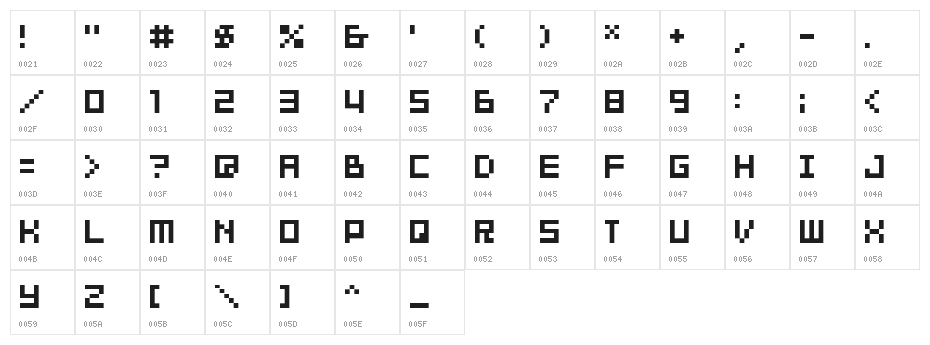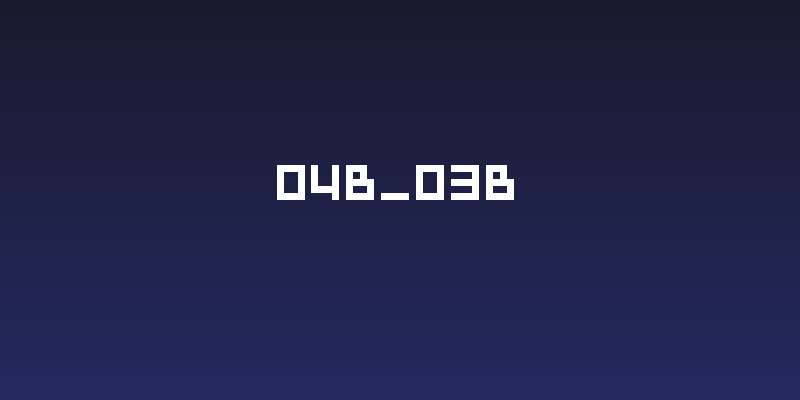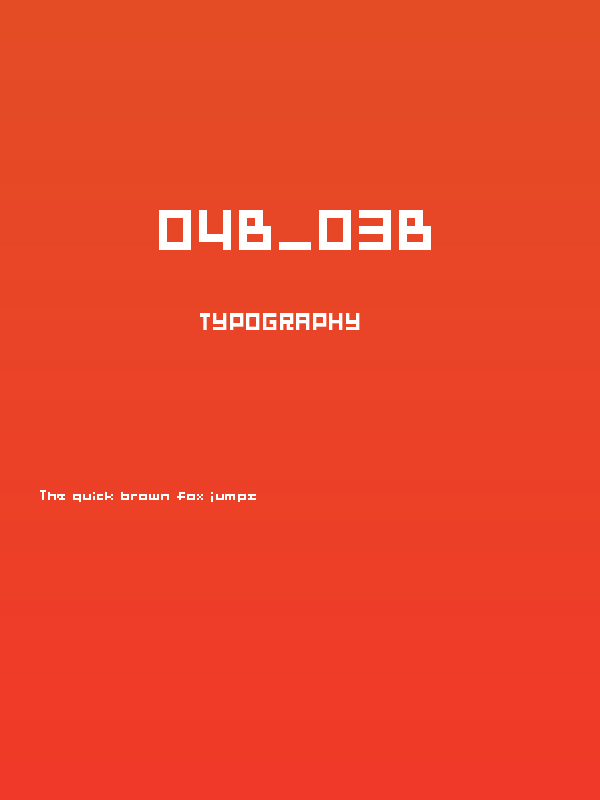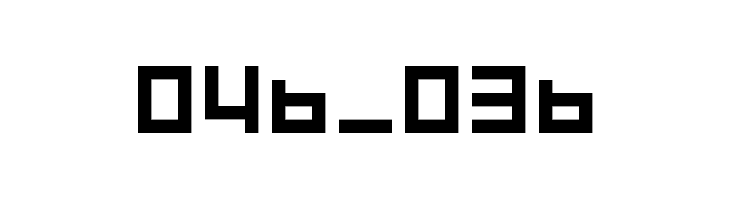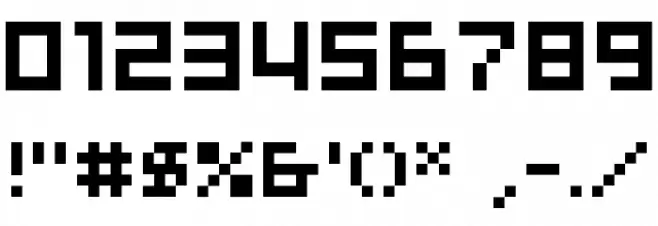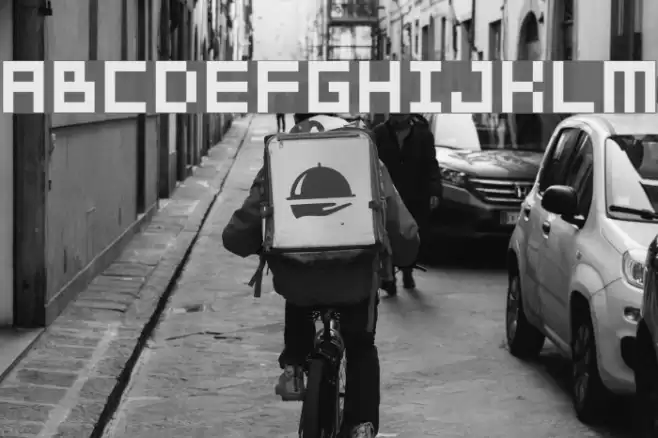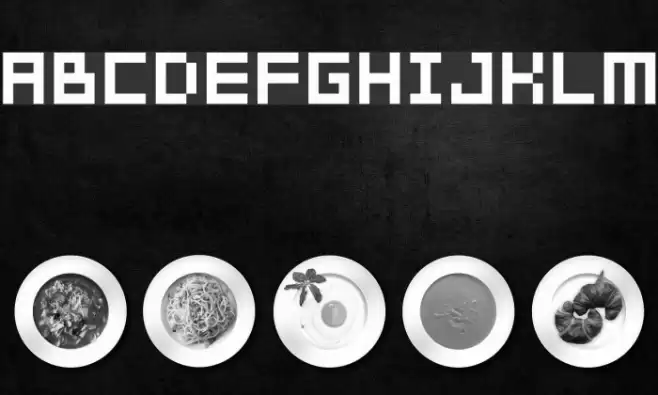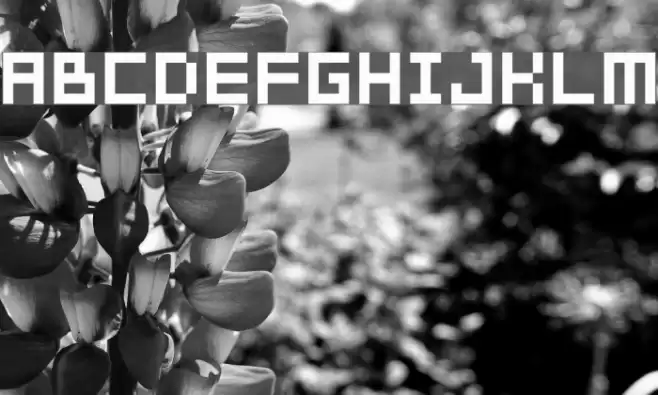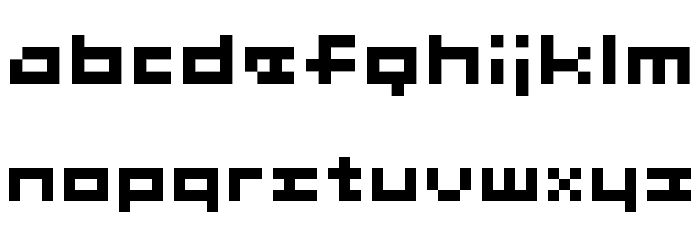
04b_03b Font
✎ Pixel
| Estilo general | Retro, Digital |
| Caso de uso | Headlines, Logos, Digital interfaces |
| Proyectos propuestos | Ideal for retro video games, digital displays, tech-themed designs, and pixel art projects. |